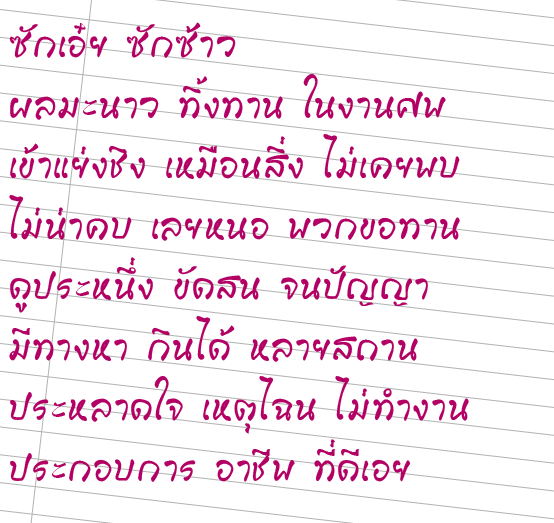
ฟอนต์ลายมือครับ ลองติชมกันครับ
ข. ไข่ เผลออ่านเป็น ช. ช้างทุกทีอะ
ลองปรับ ข.ไข่ ครับ
ช่องไฟสวยงามมากครับ สะอาดตา เจ๋ง
ทีนี้ลองเช็กภาพรวมทั้งชุดนะครับ มันจะมีบางตัวที่มาเขียนไม่ได้พร้อมกะตัวอื่น
แล้วองศาการเอียงมันจะไม่เป็นธรรมชาติ ดูแล้วจะสะดุดๆ ครับ
อย่าง ข ไข่ตัวใหม่นี่ก็ใช่
ปรับแก้ ปรับแก้
เจ๋ง
กำลังรู้สึกสะดุดว่ามันมีจุดที่บางไป บางทีก็เป็นหนาไป (แบบไม่สม่ำเสมอน่ะครับ)
แบบหัว ว แหวน จะดูหนากว่าชาวบ้าน เป็นต้น
เดี๋ยวจะไปไล่ไม่ให้สะดุดเท่าไหร่นะครับ
เพราะที่จริงตั้งใจที่จะทำให้ไม่สม่ำเสมออยู่แล้ว
จะพยายามปรับโดยไม่ให้เสียในสิ่งที่ตั้งใจไว้นะครับ
เรื่องเส้นหนาไม่เท่ากัน ปรับเฉพาะบางจุดที่หนาเกินไปพอนะ อย่าแก้เยอะ มันเป็นเอกลักษ์สวยดี
ชอบตัวเอียงมากด้วย  เจ๋ง
ผมเข้าใจเจตนาว่าไม่อยากให้เส้นสม่ำเสมอครับ
ผมหมายถึงว่า ในความหนา-บาง ของมันก็ต้องมีระบบอะไรบางอย่างให้มีความกลมกลืนน่ะครับ
เช่น หัว ว แหวน ที่ผมบอก จะใช้ระบบเดียวกับหัวของ ล ลิง, อ อ่าง ใช่ไหมครับ
อะไรประมาณนั้นครับ  เจ๋ง
เข้าใจครับ พยายามปรับแก้อยู่ครับ  ฮี่...